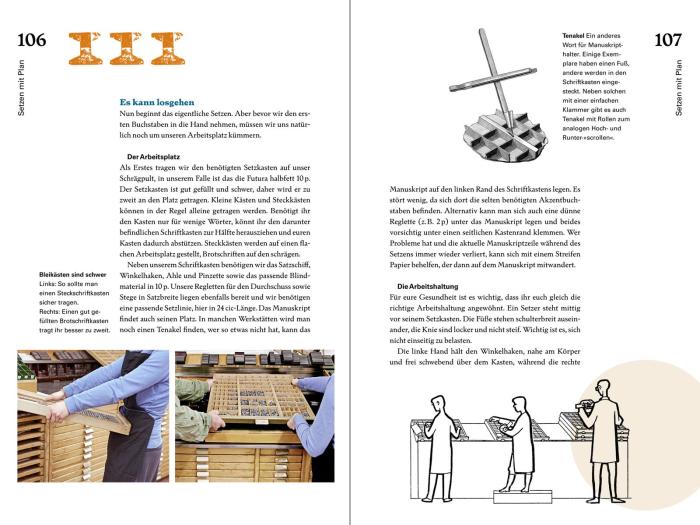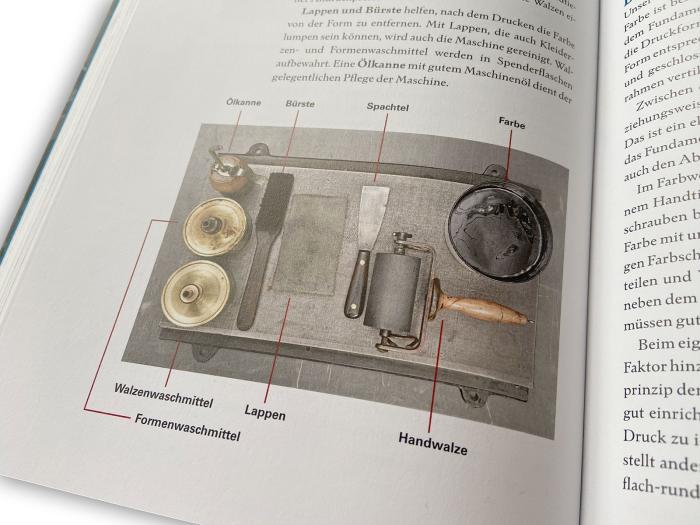
Wer heute noch in den Buchdruck mit beweglichen Lettern einsteigen möchte, hat es nicht unbedingt leicht. Die entsprechende Ausbildung gibt es schon seit Jahrzehnten nicht mehr und auch die zugehörigen Fachbücher sind nur noch antiquarisch zu bekommen. Auch wenn deren Inhalte natürlich weiter richtig sind, entsprechen sie in der Aufmachung nicht unbedingt mehr den heutigen Ansprüchen bzw. werden sie den neuen Zielen nicht vollends gerecht. Denn wer heute in den Bleisatz einsteigt, tut dies in der Regel eher aus der Freude an der Sache und weniger im Sinne einer klassischen, mehrjährigen Berufsausbildung. In diese Lücke stößt nun das neue Einsteigerbuch »Bleisatz: ein Werkstattbuch« aus dem »Rheinwerk Verlag«. Geschrieben wurde es von Heike Schnotale, die eine Schriftsetzerausbildung in Dresden absolviert hat, und Michael Wörgötter, Typografie-Professor in Augsburg.
Auf über 300 farbigen Seiten wird das Thema Bleisatz von der Gestaltung, über den Satz bis hin zum Druck fachkundig erläutert. Das Buch gliedert sich dabei in folgende Kapitel:
In der Werkstatt
Schrift über Schriften
Setzen mit Plan
Druckformen bauen
Papier und mehr
Farben und Hilfsstoffe
Die Druckpresse
Es werde gedruckt!
Weiterverarbeitung
Eingestreut sind zusätzliche Themen, Erklärungen und Beispiele aus der historischen und aktuellen Welt der Druckkunst, die jeweils nach einem der obigen Kapitel erscheinen. Zum Beispiel: »Gebrochene Schriften«, »Von Matern und flüssigem Blei« und »Experimentelle Gestaltung – Dafi Kühne«.
Fazit: Das Buch kann auf ganzer Linie überzeugen. Schritt für Schritt wird man durch alle Arbeitsbereiche des Buchdrucks geführt. Die reiche Bebilderung macht es dabei einfach, den Beschreibungen zu folgen. Dabei geht es durchaus praktisch zur Sache. Das Buch ist für jene geschrieben, die Bleisatz tatsächlich ausführen wollen. Die Erklärungen sind dazu zumindest für den Einstieg hinreichend didaktisch und detailliert genug. Eine komplette Schriftsetzerlehre lässt sich freilich nicht in ein solches Buch packen.
Die Zielgruppenbestimmung gestaltet sich im Gegensatz zu den meisten Büchern in unserem Buchverzeichnis etwas schwierig. Denn als klassisches Handwerk ist der Satz mit beweglichen Lettern kaum etwas, was man sich einfach aus einem Buch aneignen könnte. Die vielen Handgriffe müssen vorgeführt und unter Anleitung ausprobiert werden. Ganz zu schweigen davon, dass man sich die unzähligen nötigen Materialien nicht ohne Weiteres beschaffen kann. So ist das Buch also vor allem begleitend zu empfehlen. Man denke an Studenten an Hochschulen mit Bleisatz-Werkstatt oder regelmäßige Besucher einer der vielen kleinen Bleisatz-Druckereien und -Museen im deutschsprachigen Raum, die sich weiter in die Materie vertiefen wollen.